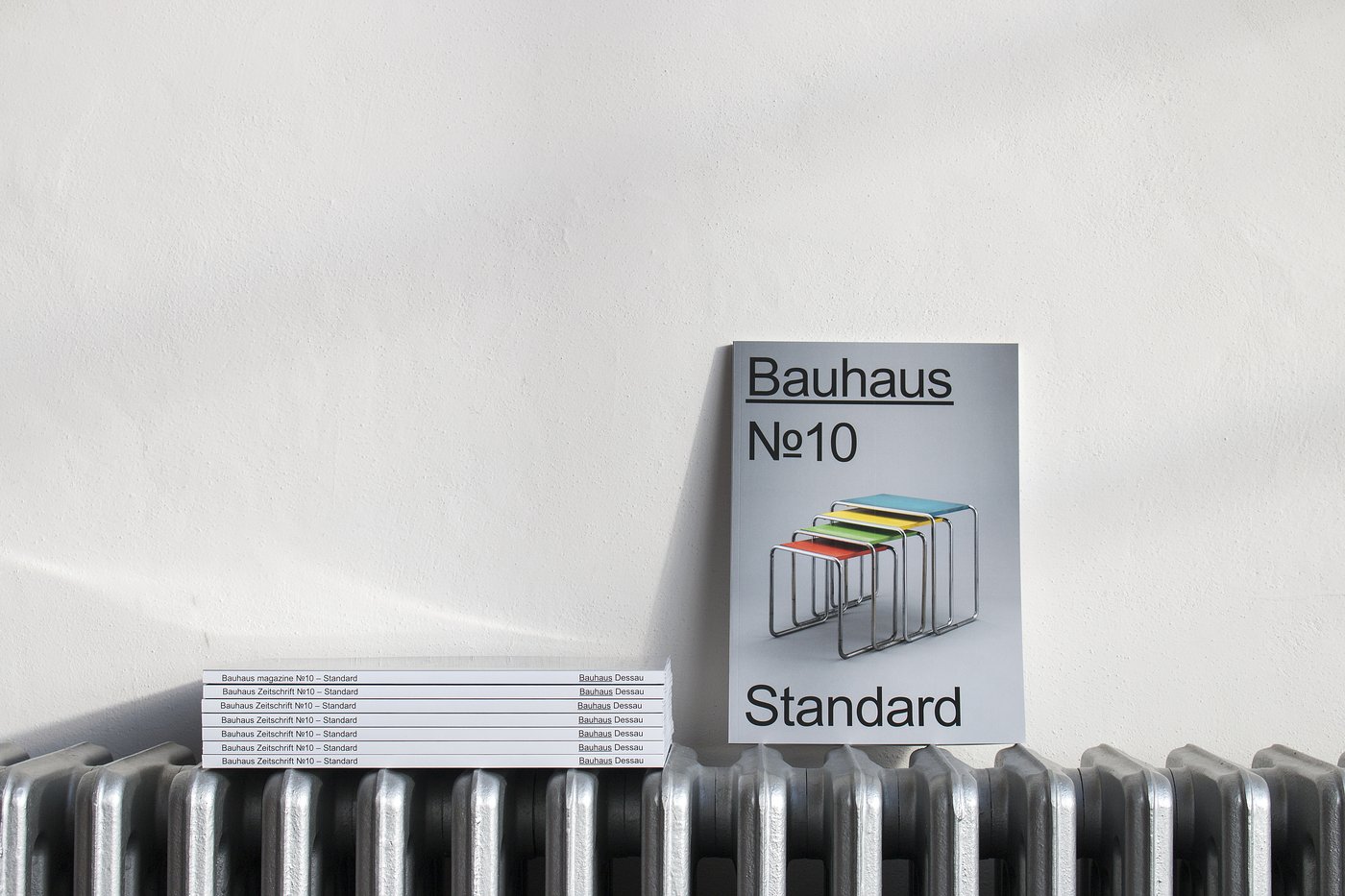
Die Zeitschrift Bauhaus 10 – Standard widmet sich dem Jahresthema „Standard“ der Stiftung Bauhaus Dessau aus historischer und zeitgenössischer Perspektive. Die Zeitschrift ist selbst ein typografisches und gestalterisches Experiment: radikal reduzierte Gestaltung von normierten Elementen bis hin zu nur einer Schriftgröße.
Typen, Normen und „Benchmarks“ bestimmen unseren Alltag. Standards machen vergleichbar, aber auch gleich, setzen Maßstäbe und werden immer wieder neu verhandelt. Vor allem am Bauhaus Dessau strebte man nach Standardisierung in Architektur und Gestaltung. Bauhaus 10 greift das Jahresthema „Standard“ der Stiftung Bauhaus Dessau sowohl aus historischer als auch aus zeitgenössischer Perspektive auf. Das Heft trifft auf Typenmöbel und Typenbühnen, Wohnmodule und Universalknoten, DIN-Erfinder und Norm-Verwalter und nähert sich mit Architekten und Künstlern aktuellen „Standard-Fragen“.
Die Zeitschrift selbst ist ein typografisches und gestalterisches Experiment mit Standards. Die Gestalter der Agentur Herburg Weiland haben ausschließlich mit normierten Elementen gearbeitet: DIN-Formate, automatische Zeilenabstände, die Verwendung ausschließlich der Systemschrift Arial in nur einer Schriftgröße – von der Überschrift, zum Fließtext, der Bildunterschrift, der Pagina bis hin zur Fußnote.
Sonja Vogel von der Stiftung Bauhaus Dessau sprach mit Tim Ising von der Münchner Agentur Herburg Weiland, die nicht nur die Reihe der Zeitschrift Bauhaus entsprechend des jeweiligen Themas gestaltet, sondern auch das Corporate Design der Stiftung Bauhaus Dessau entwickelt hat.
Sonja Vogel, Stiftung Bauhaus Dessau: Lieber Tom Ising, die Zeitschrift Bauhaus 10 setzt sich mit dem Jahresthema der Stiftung Bauhaus Dessau auseinander: Standards. Wie habt ihr dies in der Gestaltung umgesetzt?
Tom Ising: Nicht nur bei der Gestaltung des Magazins sondern auch im gesamten Corporate Design, das wir für die Stiftung Bauhaus Dessau entworfen haben, spielt das Thema Standard eine wichtige Rolle. Das Corporate Design setzt sich aus normierten Elementen zusammen. Wir verwenden nur DIN-Formate, automatische Zeilenabstände und setzen ausschließlich die Systemschrift Arial ein.
Das historische Bauhaus war ja nicht nur eine Schule, sondern stand damals wie auch heute noch für eine bestimmte Haltung: die Welt immer wieder neu zu denken und dabei eine Plattform für visionäre Ideen zu bieten. Das Corporate Design spiegelt diese Haltung wider. Seine extrem reduzierte Gestaltung bietet eine ideale Projektionsfläche, auf der neue Ideen entwickelt und international verständlich gemacht werden können. Im Sinne des historischen Bauhauses verfolgt es so den Anspruch universell verständlich zu sein und auch im 21. Jahrhundert jeden mit seiner Botschaft erreichen zu können.
Auf den ersten Blick erscheint die Zeitschrift durch Reduktion und Beschränkung ja sehr simpel. Was waren die Herausforderungen in der Umsetzung?
Tom Ising: Gerade dieser Verzicht auf dekorative Elemente wie Farben, andere Schriften und besonders auffällige Auszeichnungen macht das Magazin interessant. Man kann sich sehr gut auf die Inhalte konzentrieren. Wir zeigen, dass es auch möglich ist, eine gut durchdachte Heftordnung zu schaffen, indem man die Gestaltungsgrenzen so eng steckt.
Ein sehr wichtiges Element der Zeitschrift 10 ist die einheitliche Typografie. Auch das historische Bauhaus war bekannt für typografische Experimente. Was ist hier das Besondere an der Zeitschrift?
Tom Ising: Wir wollten das Thema Standards typografisch verstärken, indem wir im Gegensatz zu den letzten Ausgaben auf verschiedene Schriftgrößen verzichtet haben. Im gesamten Heft gibt es nur eine Schriftgröße: Arial regular in 10,8 pt. Von der Überschrift, zum Fließtext, der Bildunterschrift, der Pagina bis hin zur Fußnote. Diese Beschränkung auf nur eine Größe war eine tolle Herausforderung an die Heftgestaltung und ist unserer Meinung nach auch sehr gut gelungen!
Zeitschrift Bauhaus 10 – Standard